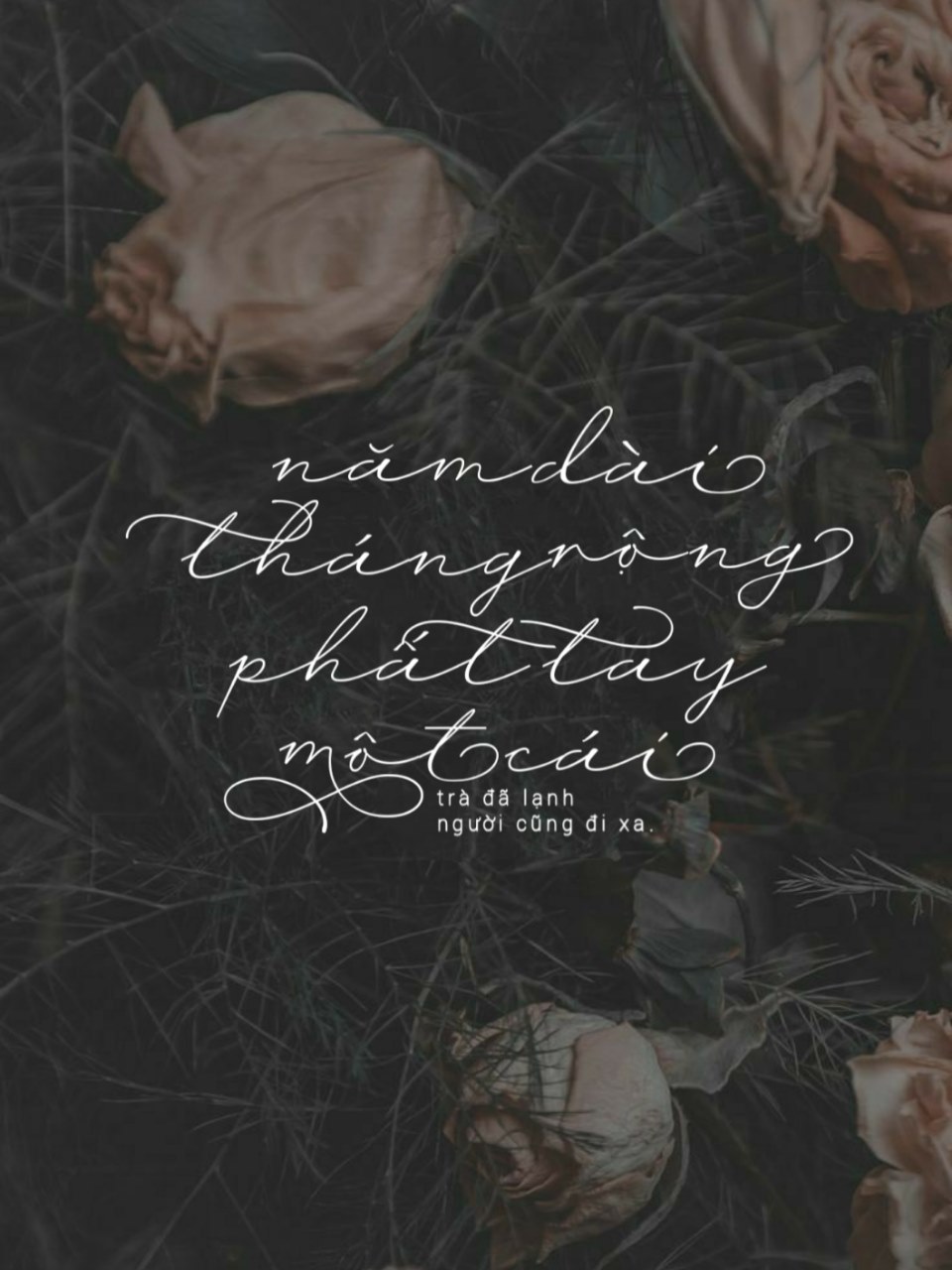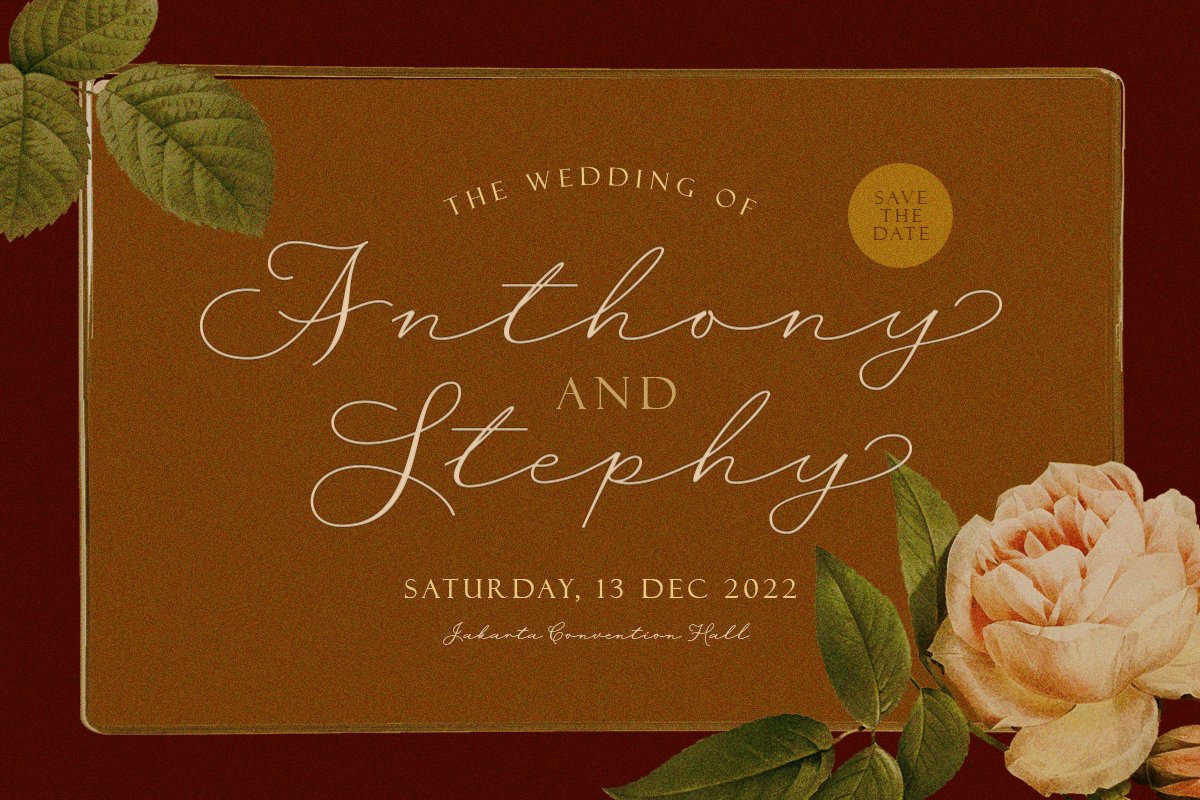
Font Wisteria Notes Việt Hóa – Font viết tay
Giới thiệu, Wisteria Notes – Một font chữ viết tay thủ công rất đẹp. Lấy cảm hứng từ chữ viết thư pháp kiểu cũ, rất sang trọng và cổ điển! Loại phông chữ này được chế tạo hoàn hảo để áp dụng đặc biệt trong logo và các hình thức trang trọng khác như lời mời, nhãn, biểu trưng, tạp chí, sách, lời chúc mừng / thiệp cưới, bao bì, thời trang, trang điểm, văn phòng phẩm, tiểu thuyết, nhãn hoặc bất kỳ loại mục đích quảng cáo.
Đây là font chữ Wisteria Notes – Modern Script Font đã được Việt Hóa đầy đủ nhé các bạn.
Demo sử dụng font Wisteria Notes Việt Hóa